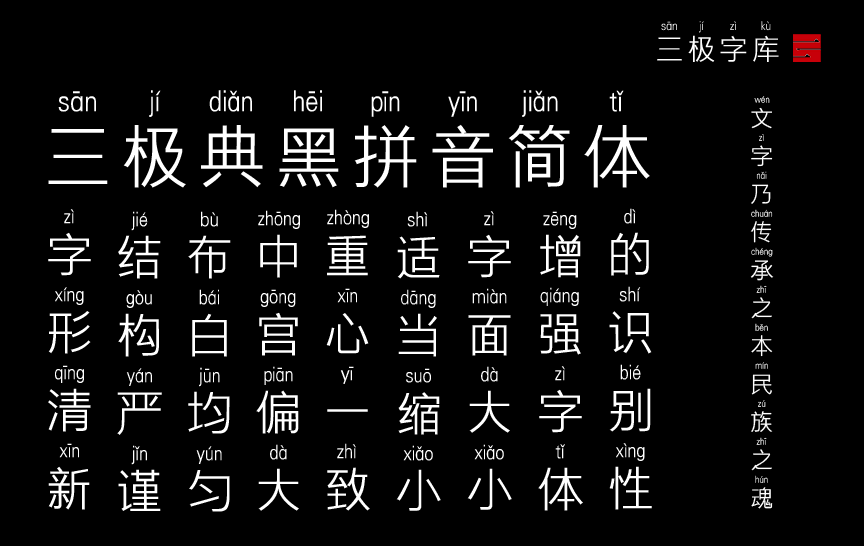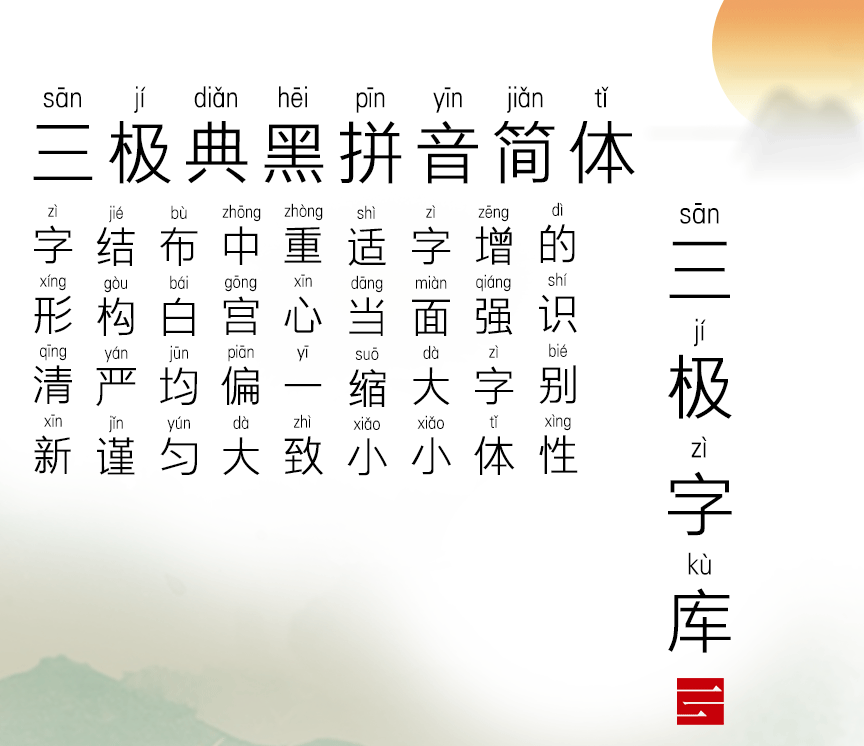
字体名称:三极典黑拼音简体
设计师:蔡建文
所属分类:黑体
三极典黑拼音简体字形清新,结构严谨,布白均匀,中宫偏大,重心一致。适当缩小字面大小、加大默认字距、增强了字体的识别性,使得版面更加通透明了。字形更加圆润秀美。适用于各类便移动端系统嵌入字体,以及传统印刷书籍正文排版。
适用媒介:报纸、杂志、书籍、广告、标志、宣传册、空间导视、包装、影视、屏幕显示、交互设计。